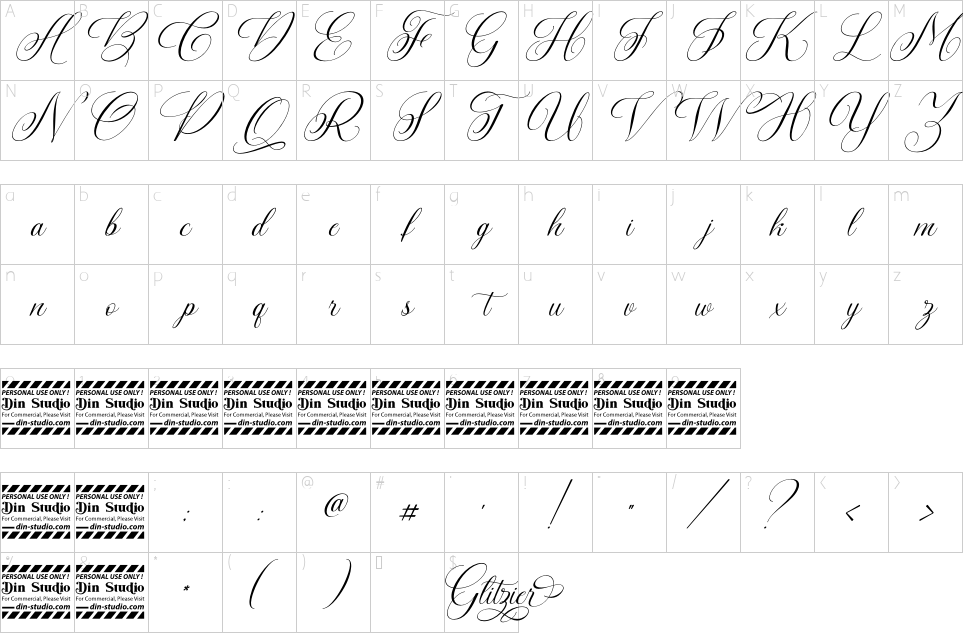
A Glitzier Font é uma elegante fonte gratuita para Windows e Mac, projetada por Din Studio. Seu design sofisticado e rico em detalhes certamente enriquecerá qualquer projeto gráfico ou design de interface com usuário que você faça. Com 2,985 downloads, a Glitzier tem se destacado como uma fonte versátil para designers profissionais que buscam um charme único para seus trabalhos. A sua disposição gratuita oferece a oportunidade de experimentar o poder da Glitzier sem preocupações financeiras. Perfect for elementos de design criativos e personalizados, ela adicionará um toque especial ao seu próximo projeto.